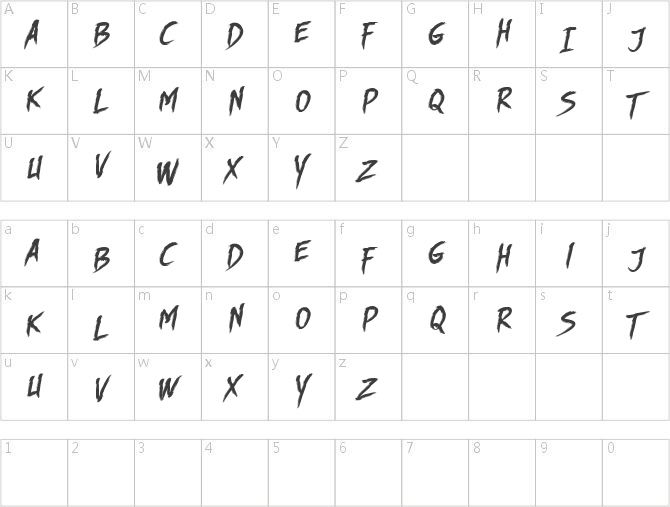
DHF-Story-Brush-Slanted
DHF-Story-Brush-Slanted介紹
DHF-Story-Brush-Slanted字體字庫(kù)是一款讓人賞心悅目、百看不厭的英文字體,適合各類(lèi)廣告和產(chǎn)品包裝設(shè)計(jì)應(yīng)用,字體大小0.11MB,格式為ttf字體,上傳用戶是曉語(yǔ)無(wú)聲,作者/版權(quán)方為未知